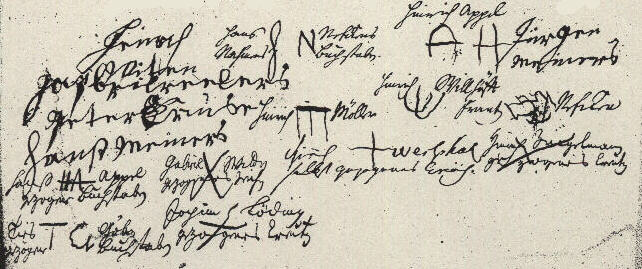
Sichere Schrift / sure handwritingHans Meiners (Hanß Meiners) |  |
| Jürgen Meiners |  |
| Hinrich Witten (für Daniel Willhöfft) |  |
Unsichere Schrift / unsure handwritingPeter Kruse (Peter Cruse verbessert/corrected : Kruse) |  |
| Gabriel Reeders "gapbrilreeders" |  |
Initialen und Hausmarken Initials and house marksHans Appel (eigenhändig) gezogene Buchstaben H A noted: "own hand made letters" |  |
| Hinrich Appel A H |  |
Ties Göben (eigenhändig) gezogene Buchstaben T G noted: "own hand made letters" |  |
| Hinrich Möller (gezeichnetes M) |  |
| Hans Nefckens (eigenhändige) Nahmens Buchstaben ( h N ) |  |
| Frantz Nefcken (Zeichnung nicht erkennbar/unclear drawing) |  |
| Hinrich Willhöfft (gezeichnetes W) |  |
Gabriel Witten (eigenhändig) gezogenes Zeichen
(mit Widerhaken) |  |
KreuzeJochim Löding (eigenhändig) gezogenes Creutz noted: "own hand drawn cross" |  |
| Hinrich Westphal selbst gezogenes Creutz |  |
| Hinrich Zingelmann (eigenhändig) gezogenes Creutz |  |